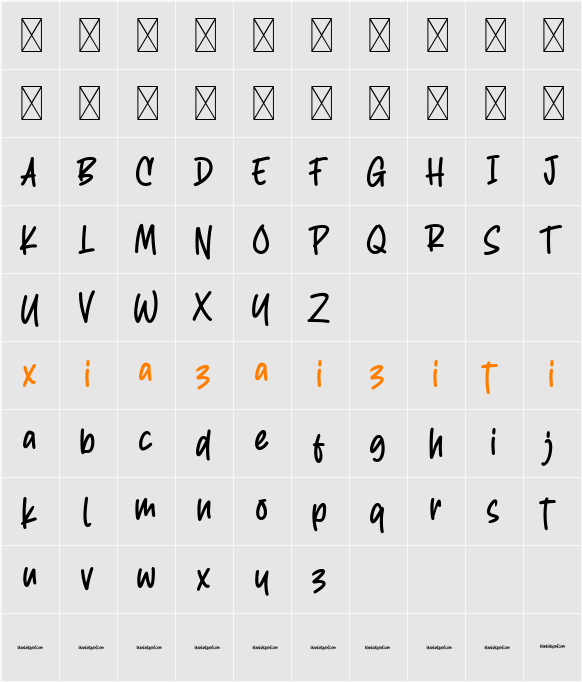
Right Howers
Right Howers,这款字体结构工整、笔画清晰,兼顾美观与易读性,适用于标题、正文、海报、包装、LOGO 等多种场景。字形优雅稳定,风格百搭耐看,适配日常排版与创意设计,让文字呈现更舒适、更具质感。Right Howers一笔一画,皆是细节,以均衡的比例、流畅的线条打造舒适视觉体验,字形端正大气,风格简约现代。无论是商业设计、品牌宣传还是日常排版,都能轻松驾驭,让文字更有格调与力量。Right Howers字体下载。